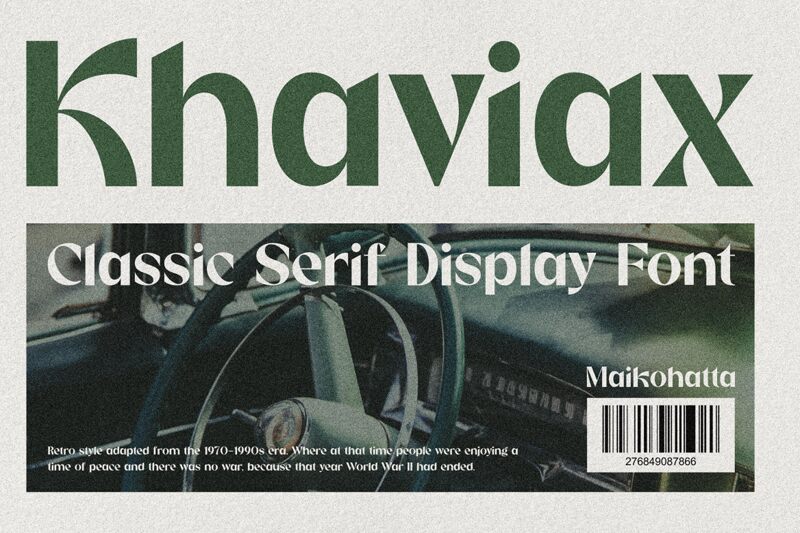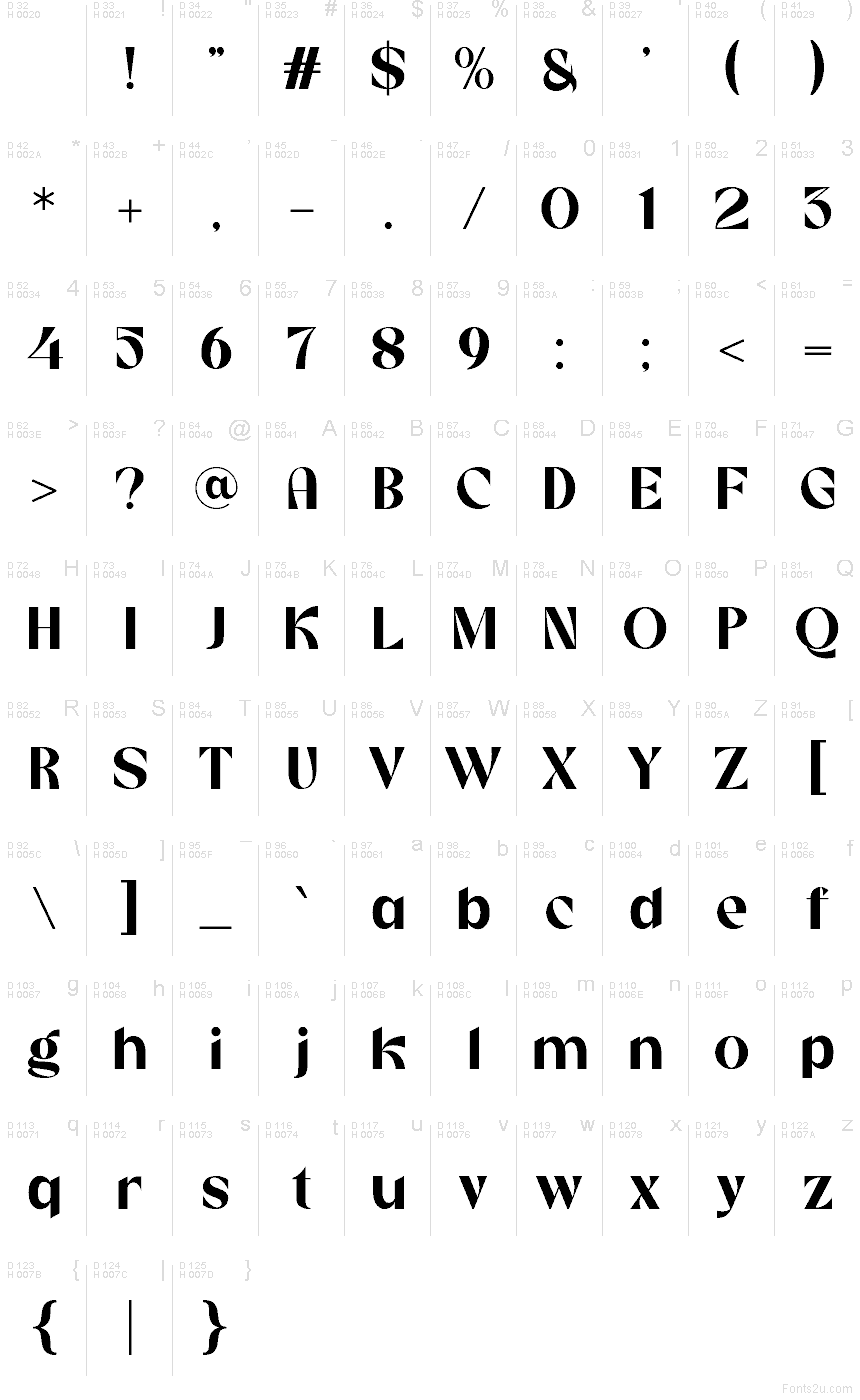
Khaviax od Maikohatta to darmowy, retro krój displayowy z eleganckim sznytem lat 70. Litery łączą wysokie, płynne krzywizny z ostrymi cięciami i kątowymi łączeniami, nadając krojowi modny rytm, który jest jednocześnie miękki i wyrazisty.
Idealnie pasuje do brandingu, tytułów na plakatach, okładek płyt, opakowań butikowych oraz nagłówków w czasopismach, wszędzie tam, gdzie krótka fraza potrzebuje stylowego, zrównoważonego charakteru. Jako darmowy font, Khaviax świetnie sprawdzi się również w projektach tytułowych i monogramach, ponieważ jego rzeźbiarskie sylwetki oraz nagłe ukośne cięcia nadają nawet kilku literom mocną, graficzną prezencję.